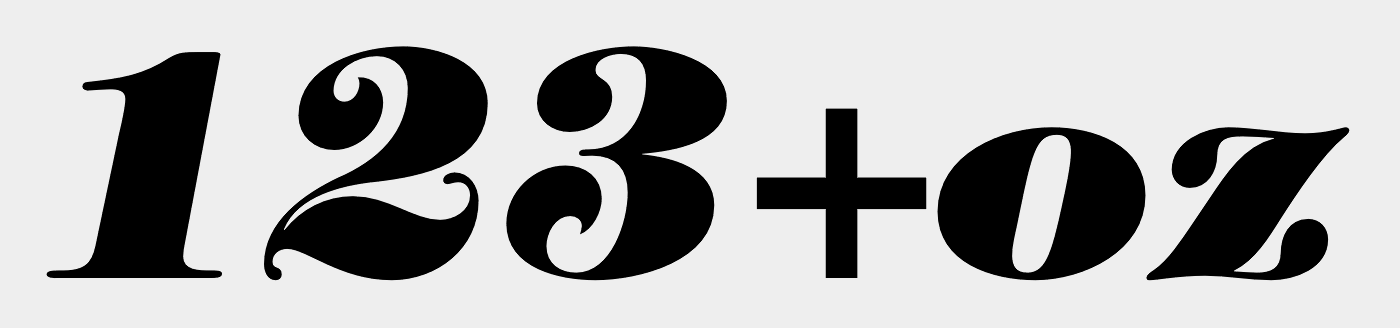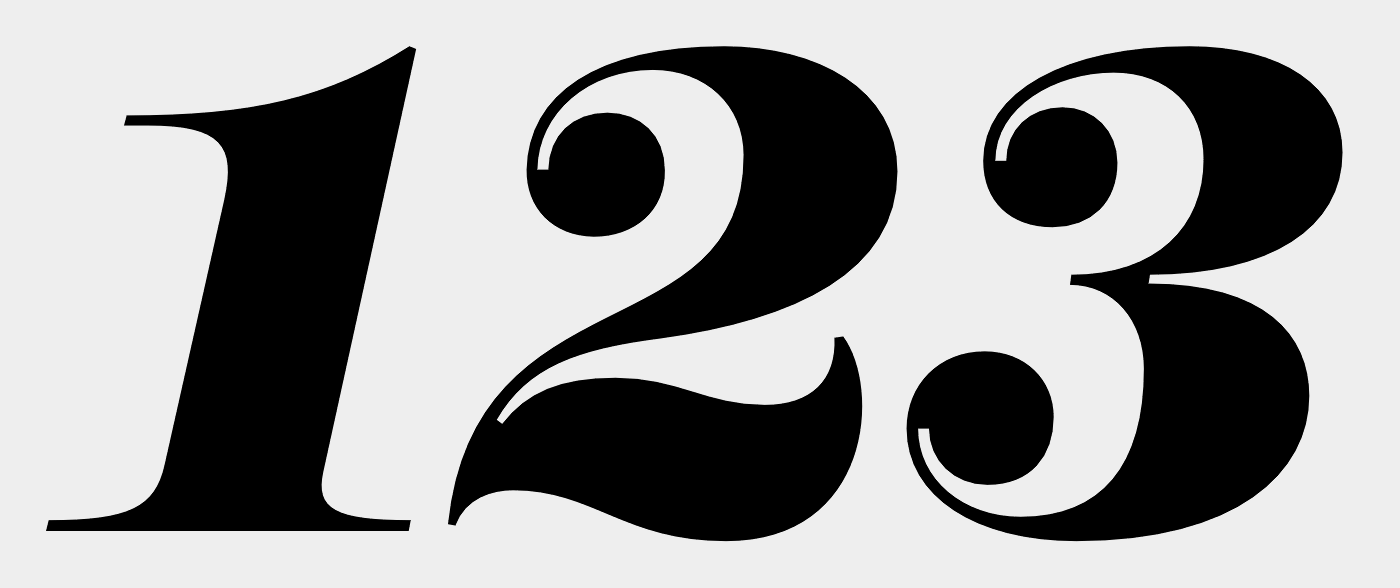
Howdy! Gesucht wird der Name der Typo auf dem angehängten Bild. Sie wurde zuletzt beim Etikett der Iron Heart Jeans gesehen. Für Hinweise aus dem Kreis der Typoexperten wäre ich sehr dankbar!!
Wahrscheinlich die Tiffany Heavy Italic. In früheren Versionen auch bei den Schriften von CorelDraw enthalten, am Anfang als „Timpani“ dann unter ihren richtigen Namen.
Die hat ja ein paar sehr ungewöhnliche Buchstabenformen!